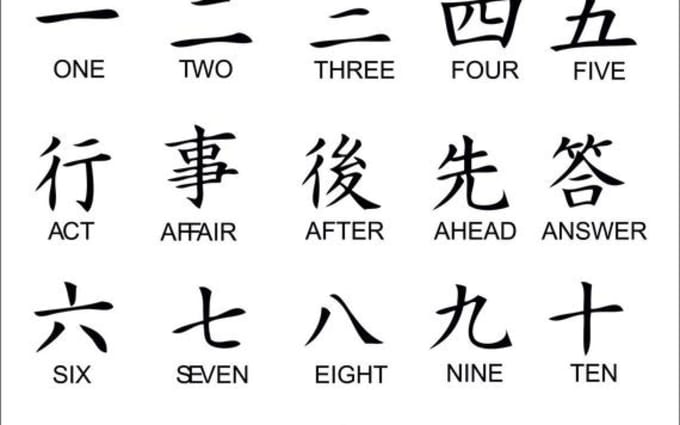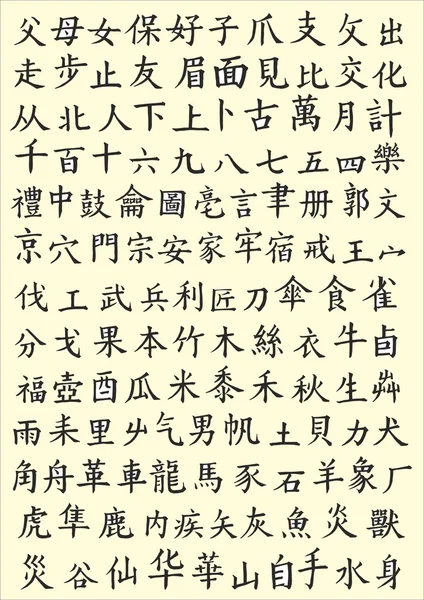
DynaComware [華康]
Гонконг. Ранее ДайнаЛаб. Создатель линейки DynaFont [金蝶]. Они являются источником текущих шрифтов Apple LiHei Pro и LiSong Pro в OS X, а также большинства шрифтов Apple для традиционного китайского языка в китайском языковом комплекте и OS 9. Они также производят шрифты MingLiU/PMingLiU и DFKai-SB, которые приходите с виндой. Совсем недавно их подразделения в Шанхае, Гонконге и Тайване работали вместе с Apple над созданием PingFang, нового системного шрифта, представленного в OS X 10.11 El Capitan.